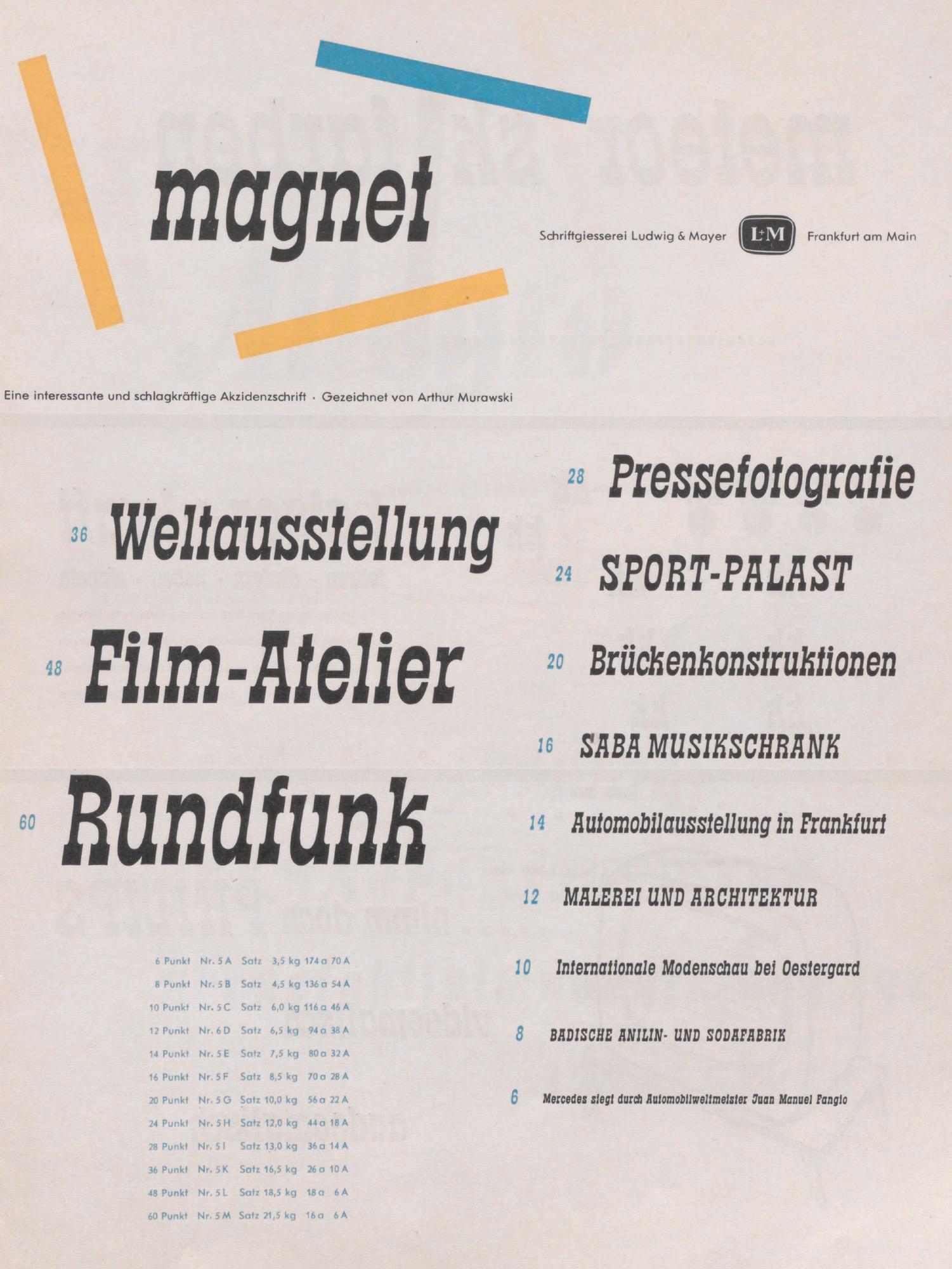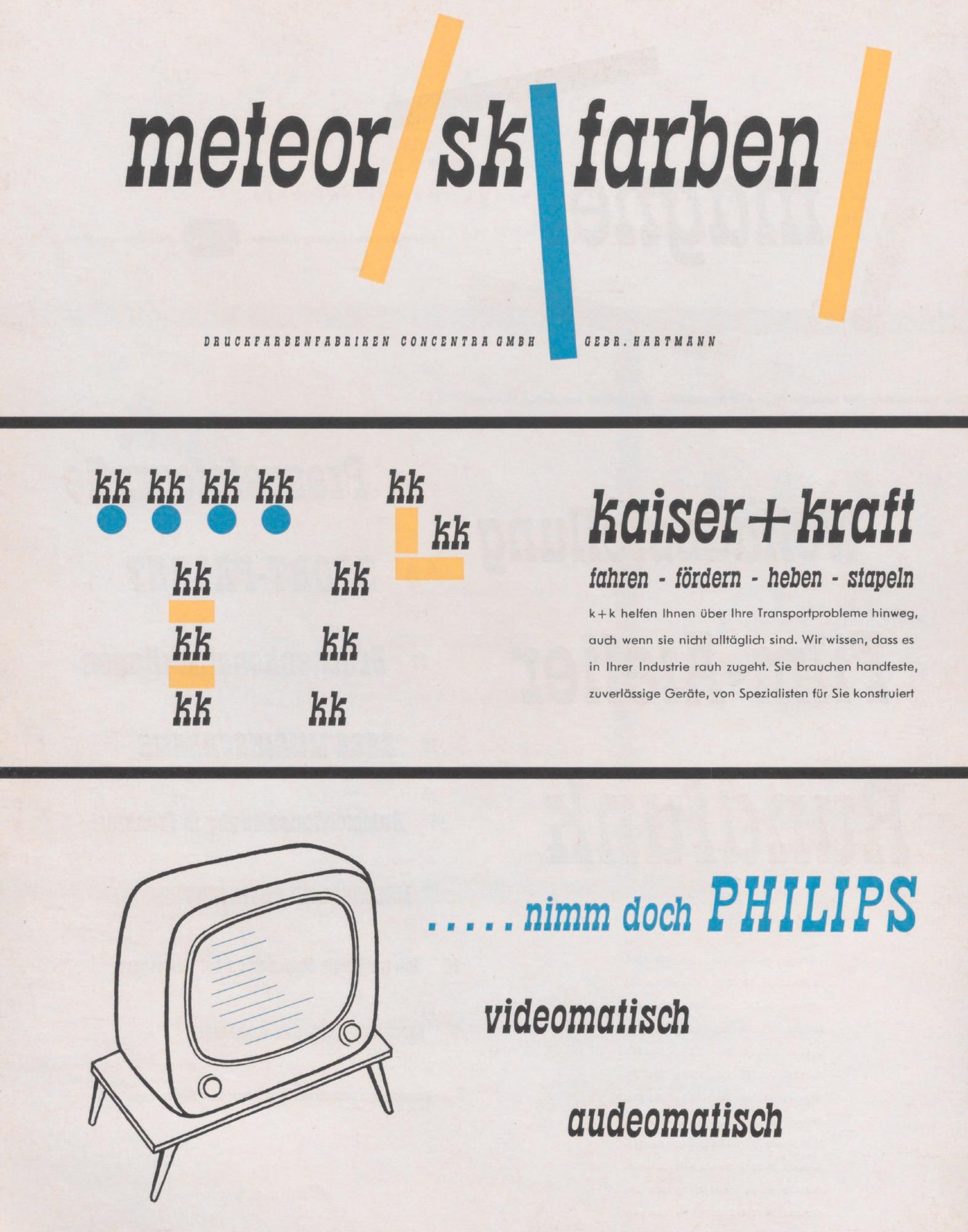
Font-Wiki: Magnet [L&M]
• circa 1953
• Serifen:
• slab
• Antiqua dekorativ
Die Magnet von Arthur Murawski erschien Anfang der 1950er-Jahre als »schlagkräftige Akzidenzschrift« bei der Schriftgießerei Ludwig & Mayer. Als Italienne bezieht sich die Magnet auf Schriften des 19. Jahrhunderts mit einer überbetonten Waagerechten und Serifen.
Eine Digitalisierung mit erweitertem lateinischen Zeichensatz gibt es als RMU Magnet von RMU Fonts.